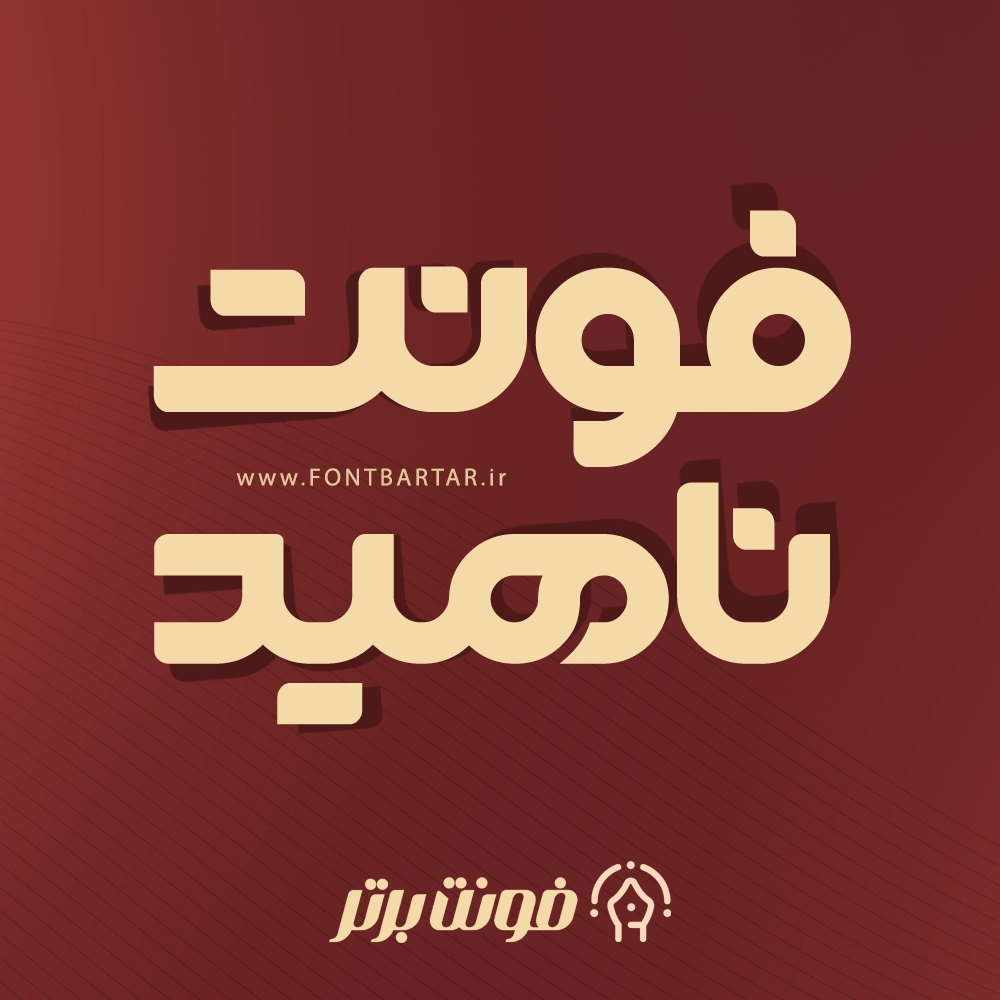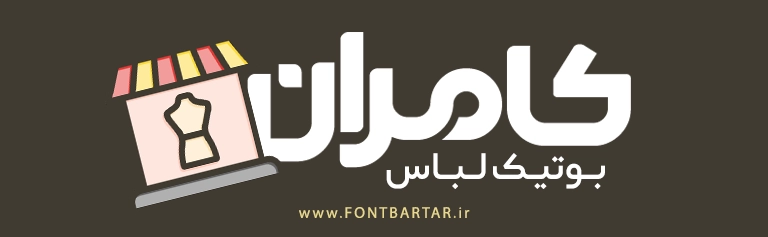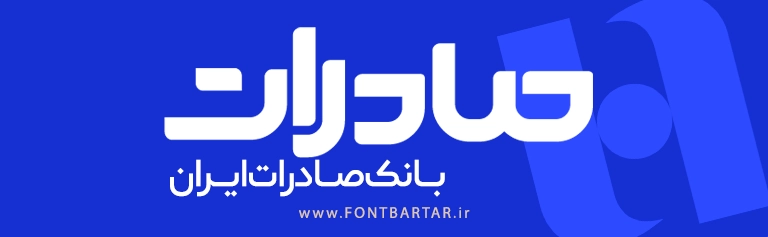
فونت خاص ناهید یکی از محبوبترین و حرفهایترین فونتهای فارسی است که بهدلیل طراحی قدرتمند، وزن زیبا و سازگاری عالی با پروژههای گرافیکی و طراحی وب، طرفداران زیادی دارد. این فونت خاص فارسی با ظاهر مدرن، ضخامت استاندارد و سبک منحصربهفرد، انتخابی ایدهآل برای طراحانی است که میخواهند کیفیت بصری پروژههای خود را ارتقا دهند.
ویژگیهای برجسته فونت خاص جدید ناهید
خرید فونت خاص ناهید ترکیبی از زیبایی، خوانایی و قدرت طراحی است. این فونت با خطوط روان، دورهای دقیق و ضخامت چشمنواز، برای استفاده در بنرها، پوسترها، لوگوتایپها، طراحی UI و تایپوگرافیهای مدرن فوقالعاده کاربردی است.
برخی از ویژگیهای این فونت عبارتاند از:
- خوانایی بالا در اندازههای مختلف
- طراحی استاندارد و چشمنواز
- مناسب برای برندینگ و لوگو
- بینظیر برای پوستر، بنر، کاور و شبکههای اجتماعی
- استایل مدرن مناسب برای تیتر و متنهای خاص
استفاده از فونت زیبا ناهید میتواند هویت بصری پروژههای شما را ارتقا داده و ترکیبی از قدرت و جذابیت در طراحی ایجاد کند.
کاربردهای فونت ناهید در طراحی حرفهای
این برای فونت زیبا پروفایل طیف وسیعی از پروژهها مناسب است، از جمله:
- طراحی کاور و بنر تبلیغاتی
- ساخت لوگوتایپ حرفهای
- طراحی پست و استوری اینستاگرام
- استفاده در تایپوگرافیهای برجسته
- طراحی وبسایت و رابط کاربری
- پوسترهای تبلیغاتی و تجاری
اگر میخواهید طراحیهایتان خاص، مدرن و حرفهای دیده شود، فونت زیبا ناهید یک انتخاب کاملاً هوشمندانه است.
FAQ – سوالات متداول درباره فونت زیبا ناهید
1. فونت ناهید برای چه نوع طراحیهایی مناسب است؟
فونت ناهید برای طراحی تیتر، پوستر، بنر تبلیغاتی، شبکه اجتماعی، لوگوتایپ و طراحی رابط کاربری بسیار عالی عمل میکند.
2. آیا فونت ناهید خوانایی مناسبی دارد؟
بله. این فونت در اندازههای مختلف خوانایی بسیار بالایی دارد و میتواند هم در تیتر و هم در بدنه متن استفاده شود.